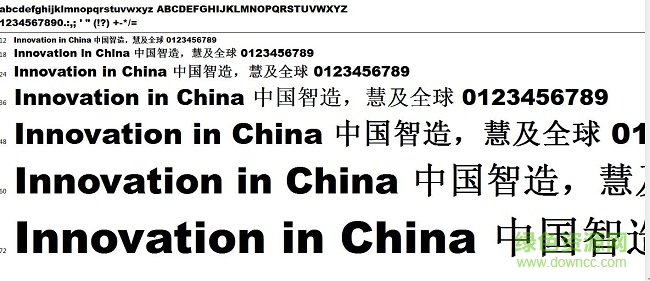
arial black常規(guī)普通西方字體
arial black 黑體 西方是一款常規(guī)普通版英文黑體字體,該字體方正飽滿,粗細(xì)相同,醒目突出,通常用在短文標(biāo)題、報(bào)刊文獻(xiàn)等領(lǐng)域,需要的小伙伴快來(lái)下載吧!
arial black 黑體 西方